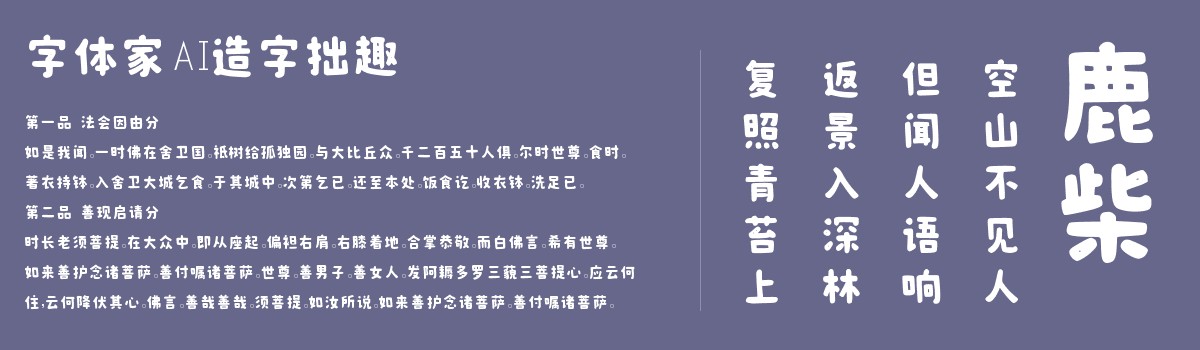
字体家AI造字拙趣
字体家AI造字拙趣是一款由字体家AI神笔造字生成的艺术字体,这款字体主笔粗壮饱满,如敦实的立柱般沉稳有力,笔画末端却藏着细腻的圆角,像被温柔打磨过的边角,消解了生硬感。结构方正端正,转折处方中融圆,直线的硬朗里透着曲线的柔和,像刚柔相济的君子,既有力量的稳重,又有温度的亲和,简洁中藏着克制的细腻,现代感十足却不冰冷。适合用于一些广告标题、平面文案、海报标题、网页广告用字的编辑。